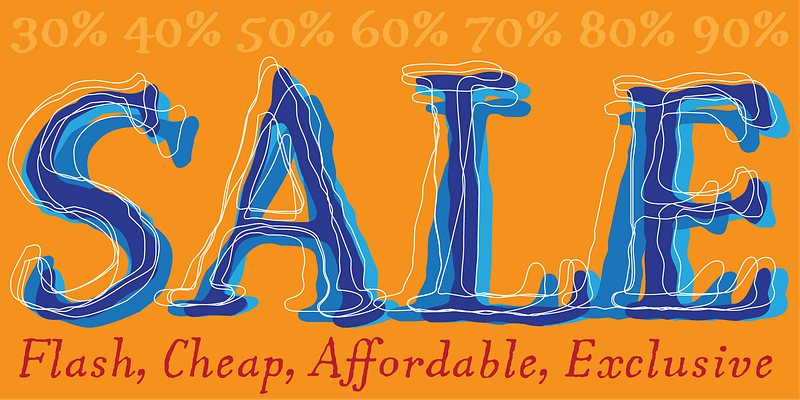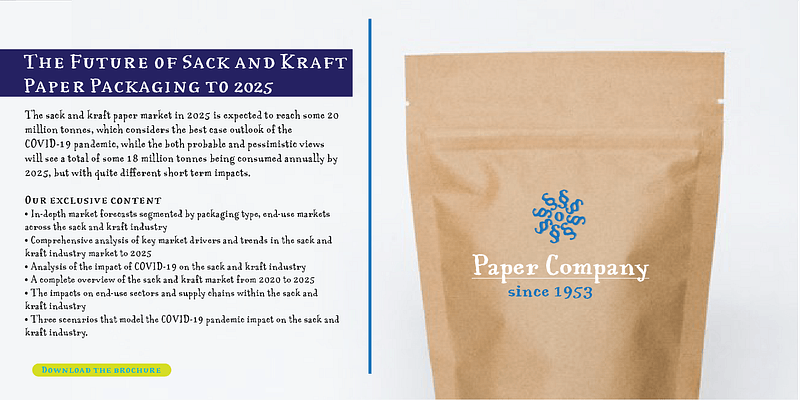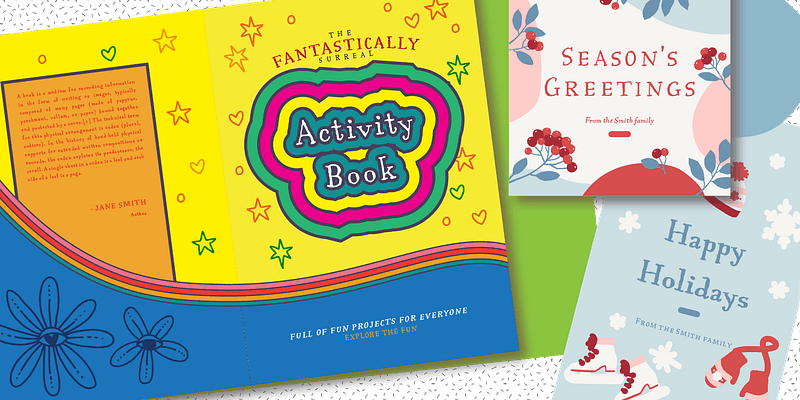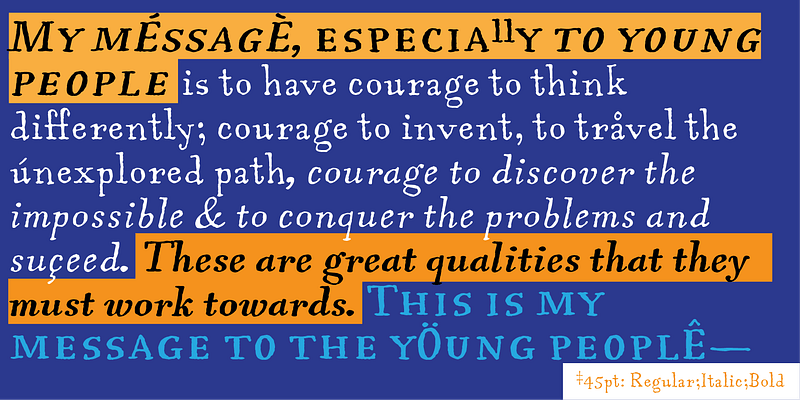
MVB Aunt Mildred hat einen Vintage-Charme, der an handgeschriebene Postkarten oder Werbung erinnert. Akemi Aoki zeichnete die Buchstaben mit einem feinen Filzstift und benannte sie nach ihrer Großtante. Seit ihrer Veröffentlichung im Jahr 1995 ist Tante Mildred eine beliebte Wahl für Kinderbücher. Vor kurzem wurden Kursiv- und Fettdruck hinzugefügt, wodurch sie sich noch besser für Publikationen, Verpackungen und Grüße aller Art eignet.